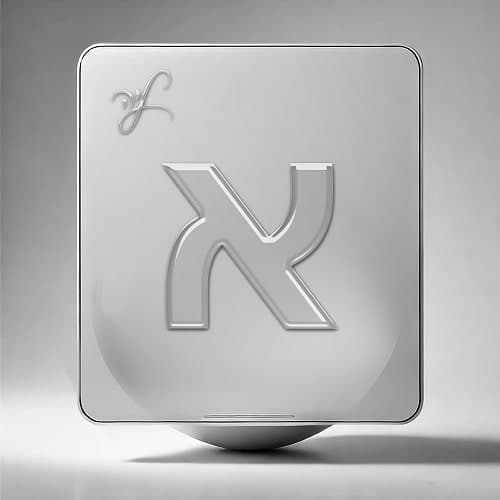
העולם הדיגיטלי והטכנולוגי, שלא מפסיק להתפתח בקצב מסחרר, מציב למעצבים ומפתחי פונטים דרישות חדשות בתחום העיצוב הגרפי.
הם נדרשים לעמוד בסטנדטים חדשים ולהמשיך לייצר פונטים יחודיים שיסייעו למעצבים בעבודתם. הם יודעים וזוכרים שאחד האלמנטים החשובים ביותר בעיצוב דיגיטלי הוא הבחירה הנכונה של פונטים.
פונטים מיוחדים בעברית יכולים להפוך את המוצר הדיגיטלי שלך להרבה יותר ייחודי מזמין, לפעמים אפילו בלתי נשכח.
פונטים בעברית להורדה הפכו היום נגישים יותר מתמיד, וזה נחמד ביותר. מגוון רחב של פונטים, החל מקלאסיים ועד מודרניים, עבור דרך סוגים רבים ומגוונים של פונטים, זמינים היום להורדה בתשלום, ורבים מהם אף בחינם.
הפונט המומלץ ביותר עבורכם תלוי בסגנון העיצוב ובקהל היעד. חשוב מאד לבחור אותו בכובד ראש ולהשקיע מחשבה ואכפתיות בבחירת הפונט המתאים הן מבחינה ויזואלית והן מבחינה תפקודית-פונקציונאלית. הוא צריך להיות יפה וגם לשרת את הטקסט בצורה המיטבית.
השאלה איך להכין פונטים בעברית זו שאלה שמעניינת ומטרידה רבים, מתוך הבנת החשיבות שבשילוב פונטים ייחודיים במוצרים דיגיטליים.
עם התוכנות המתאימות והידע הנדרש, תוכלו ליצור פונטים ייחודיים המותאמים בדיוק לצרכים שלכם. תהליך יצירת פונט דורש אמנם סבלנות ומיומנות, ועל כן אנחנו נמצאים כאן בשבילכם עם מבחר עצום.
אך אם תרצו בכל זאת ליצור בעצמכם, אל ייאוש, דעו שהתוצאה יכולה להיות מדהימה.
ובחזרה לענייננו. העתיד של הפונטים בעיצוב הטכנולוגי מבטיח מגוון רחב של אפשרויות חדשות.
פונטים אינטראקטיביים, פונטים תלת-מימדיים ופונטים המשתנים בהתאם להקשר – כל אלה הם רק חלק מהטכנולוגיות החדשות שעשויות לשנות לטובה ולשפר את האופן שבו אנו משתמשים בפונטים.
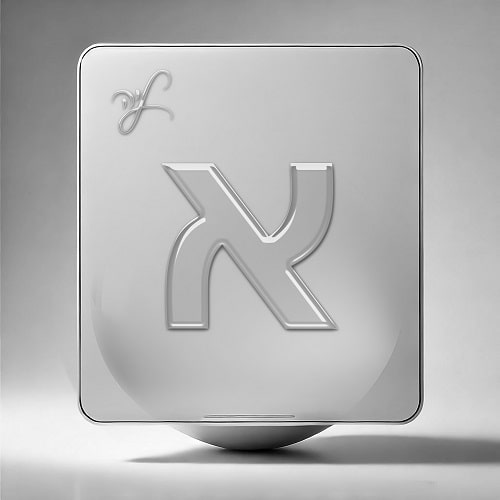
פונט רגיל הוא פונט סטנדרטי שניתן למצוא אותו במרבית המחשבים. כשתביטו על פונט והוא ייראה לכם מוכר מדי, דעו שהוא פונט רגיל.
פונט ייחודי הוא פונט שעוצב באופן אישי, ואינו זמין באופן נרחב, כזה שלא רואים אותו בכל מקום. פונטים ייחודיים יאפשרו לכם ליצור עבור הלקוחות והמותגים שלהם מראה ייחודי ומזוהה.
ישנן מספר דרכים למצוא פונטים מיוחדים בשפה העברית: